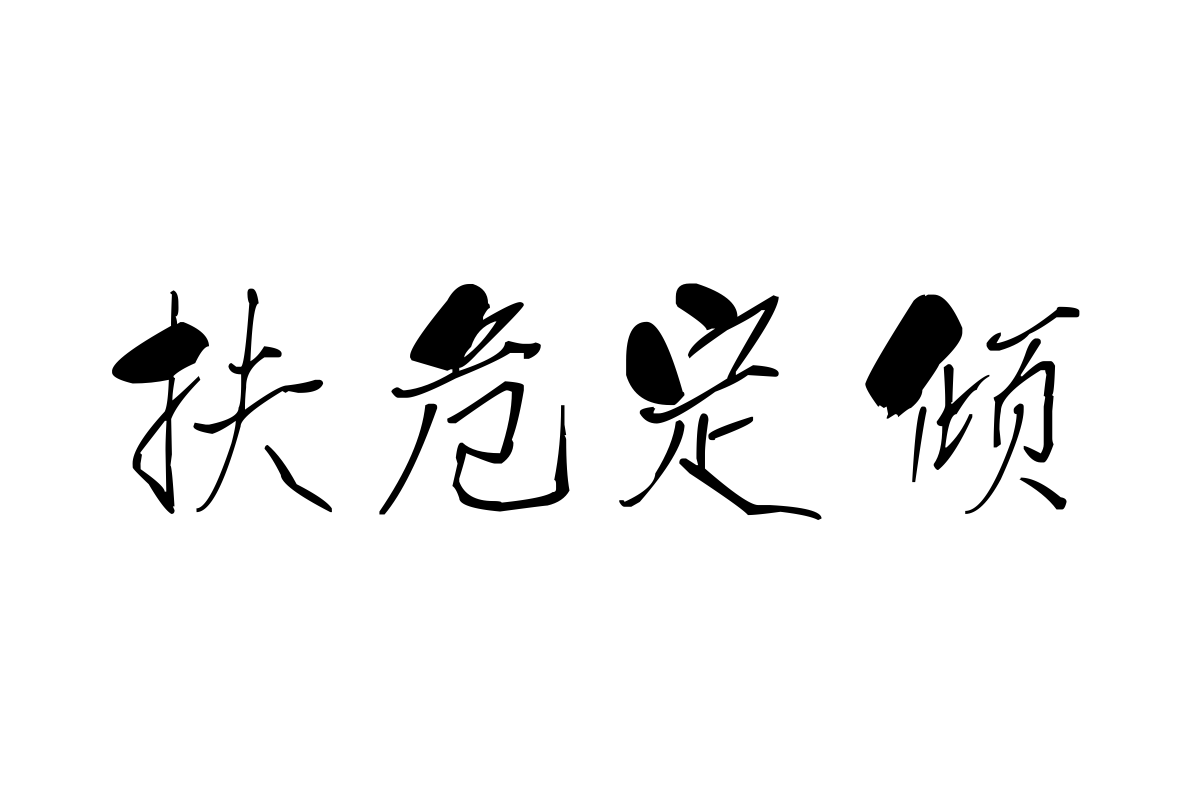
汉标精工阿叶体字体是一款由汉标精工公司设计开发的中文字体。这款字体具有独特的风格和特点,适用于各种应用场景,如广告、包装、书籍、报纸等。
汉标精工阿叶体字体的特点如下:
1. 字形独特:该字体的笔画流畅,字形独特,给人一种优雅而富有艺术感的感觉。
2. 结构紧凑:汉标精工阿叶体字体的结构紧凑,笔画之间相互关联,形成了一种和谐的整体感。
3. 适应性强:这款字体适用于多种应用场景,无论是在印刷品还是电子屏幕上都能保持良好的视觉效果。
4. 易读性高:汉标精工阿叶体字体的笔画简洁明了,易于阅读,适合用于需要快速阅读的场合。
5. 兼容性好:这款字体具有良好的兼容性,可以与其他字体进行搭配使用,创造出丰富的视觉效果。
总之,汉标精工阿叶体字体是一款具有独特风格和特点的中文字体,适用于各种应用场景,深受设计师和用户的喜爱。
汉标精工阿叶体